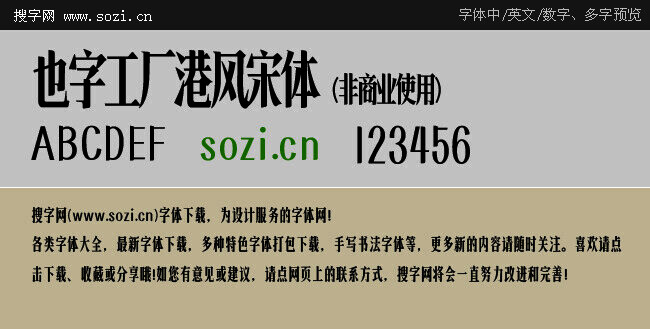
也字工厂港风宋体
搜字网给大家提供一款也字工厂港风宋体(非商业使用)中文字体下载,也字工厂港风宋体是一款宋体字体,字形瘦长,粗细对比明显,整体比较方正,笔画带有圆角,显得更加柔和,横竖笔画对比大,具有反差感和新鲜感。适合应用于海报设计、包装设计、网页设计等应用(此字体为个人非商用版,商用可以联系:官方网址:https://yefont.com/home,联系方式:13798980448)。